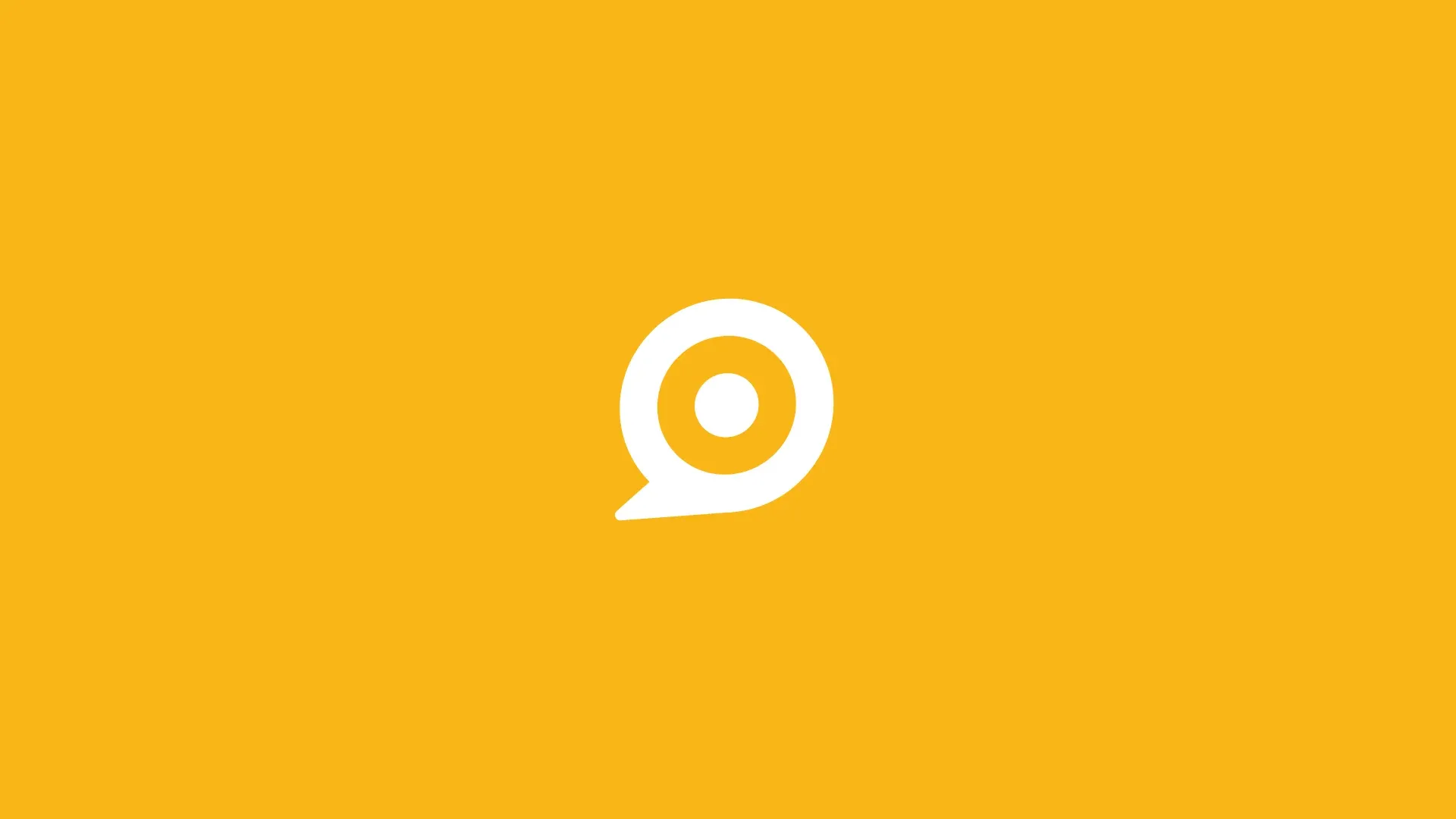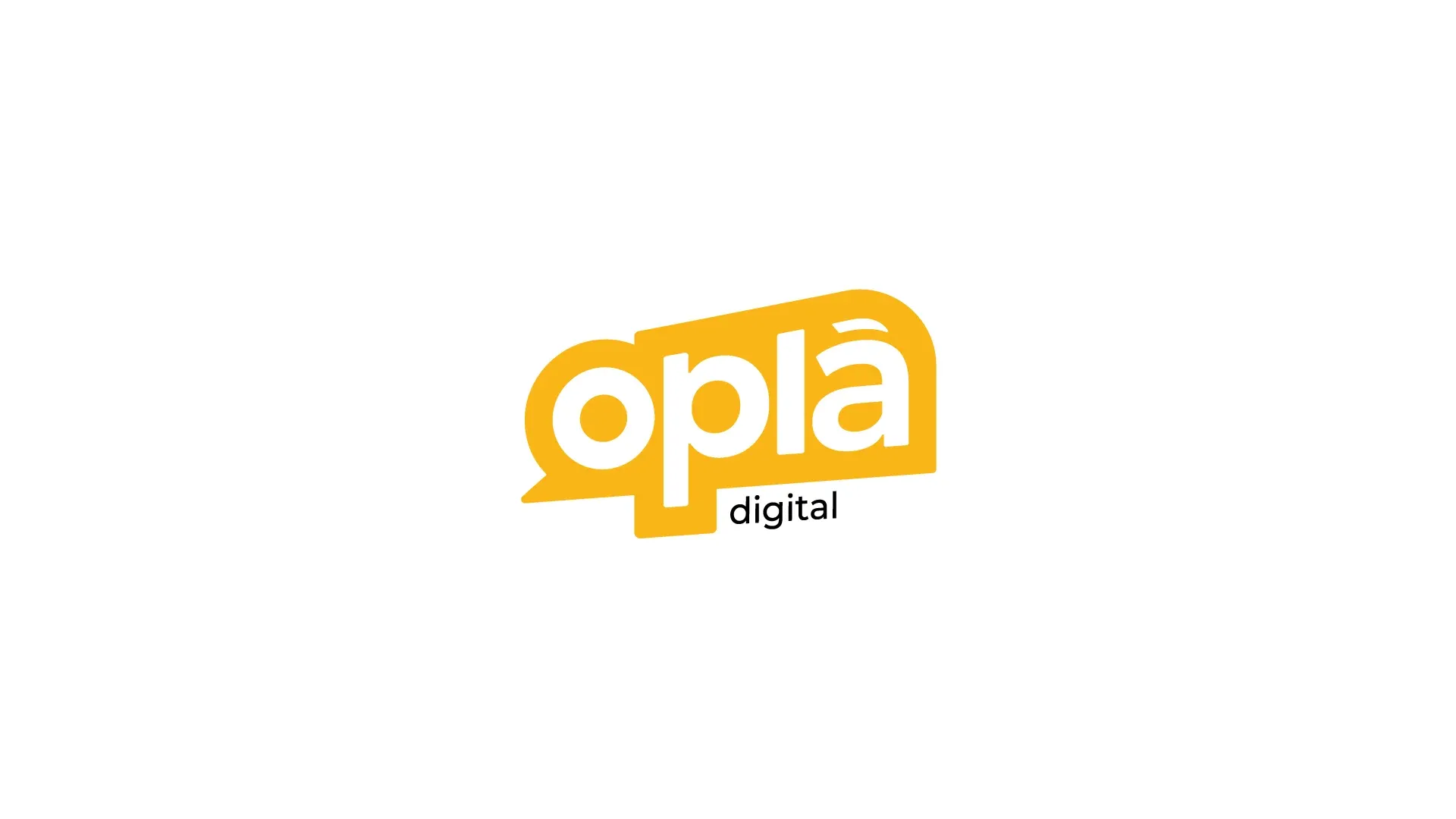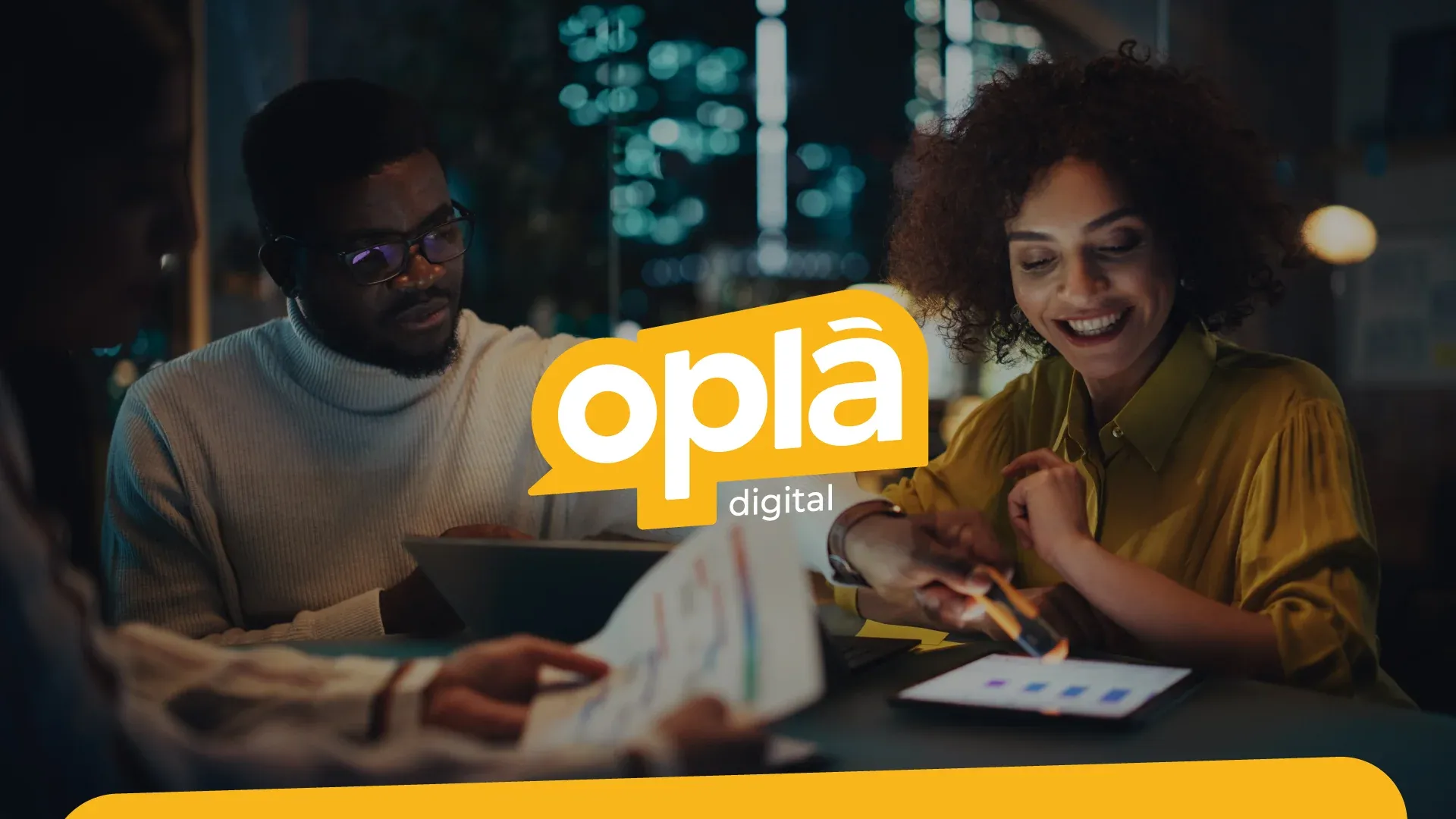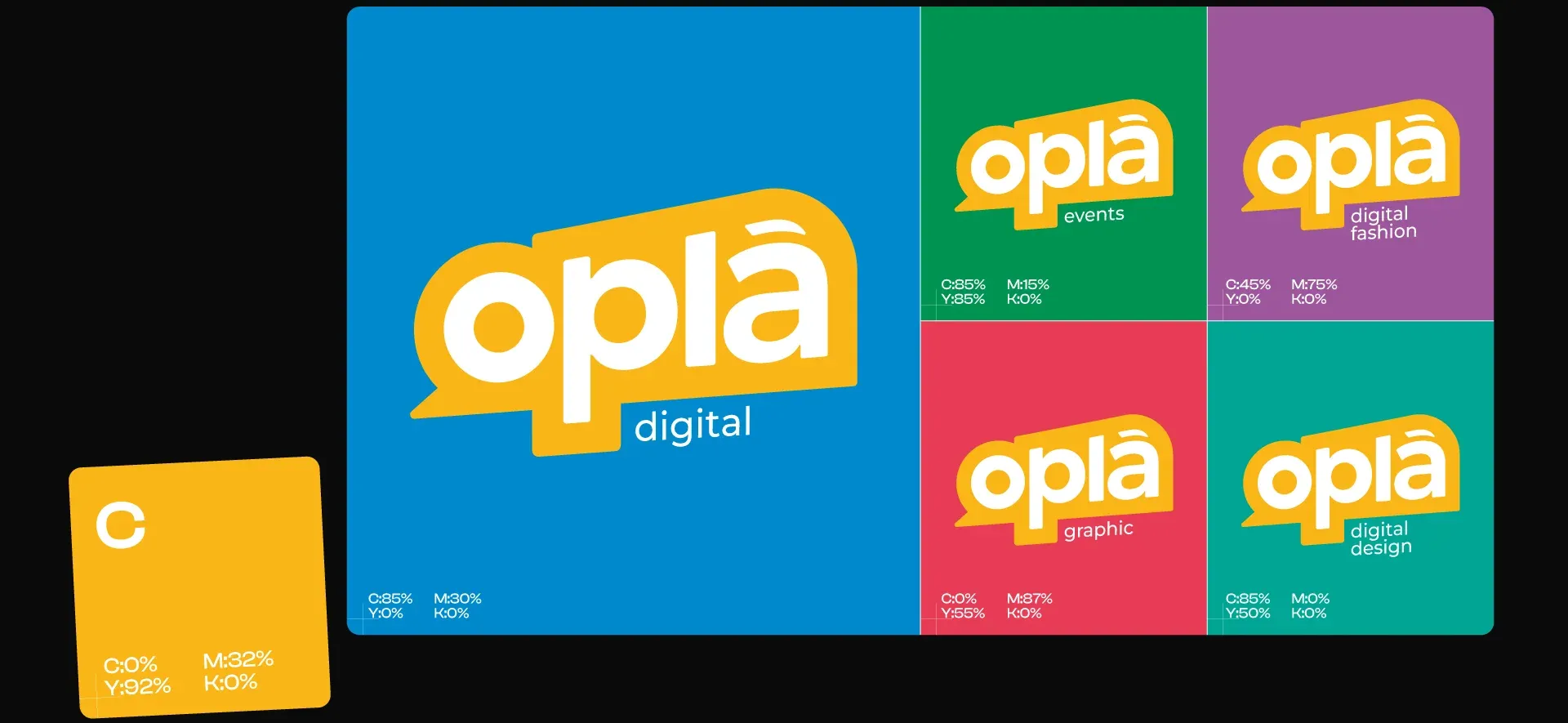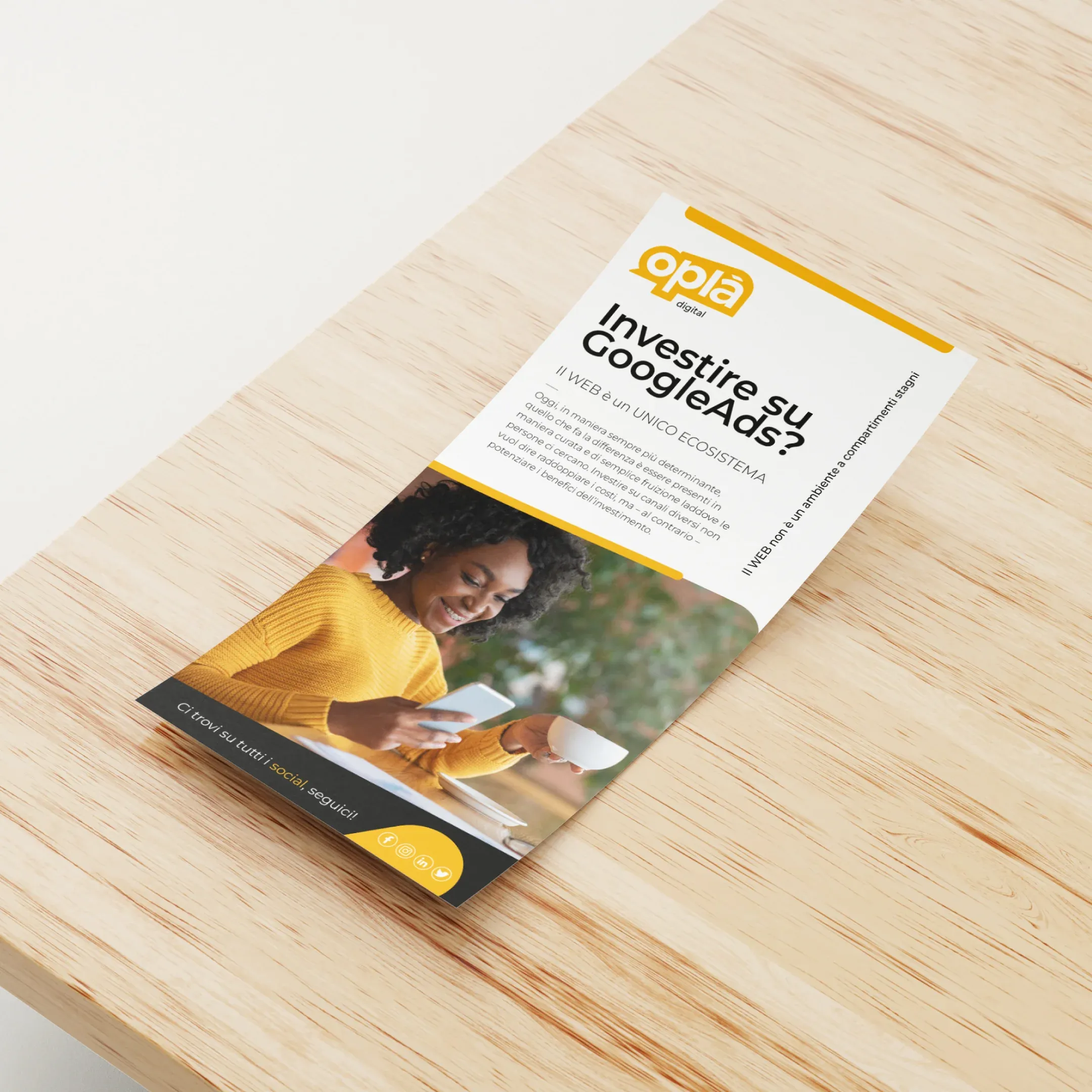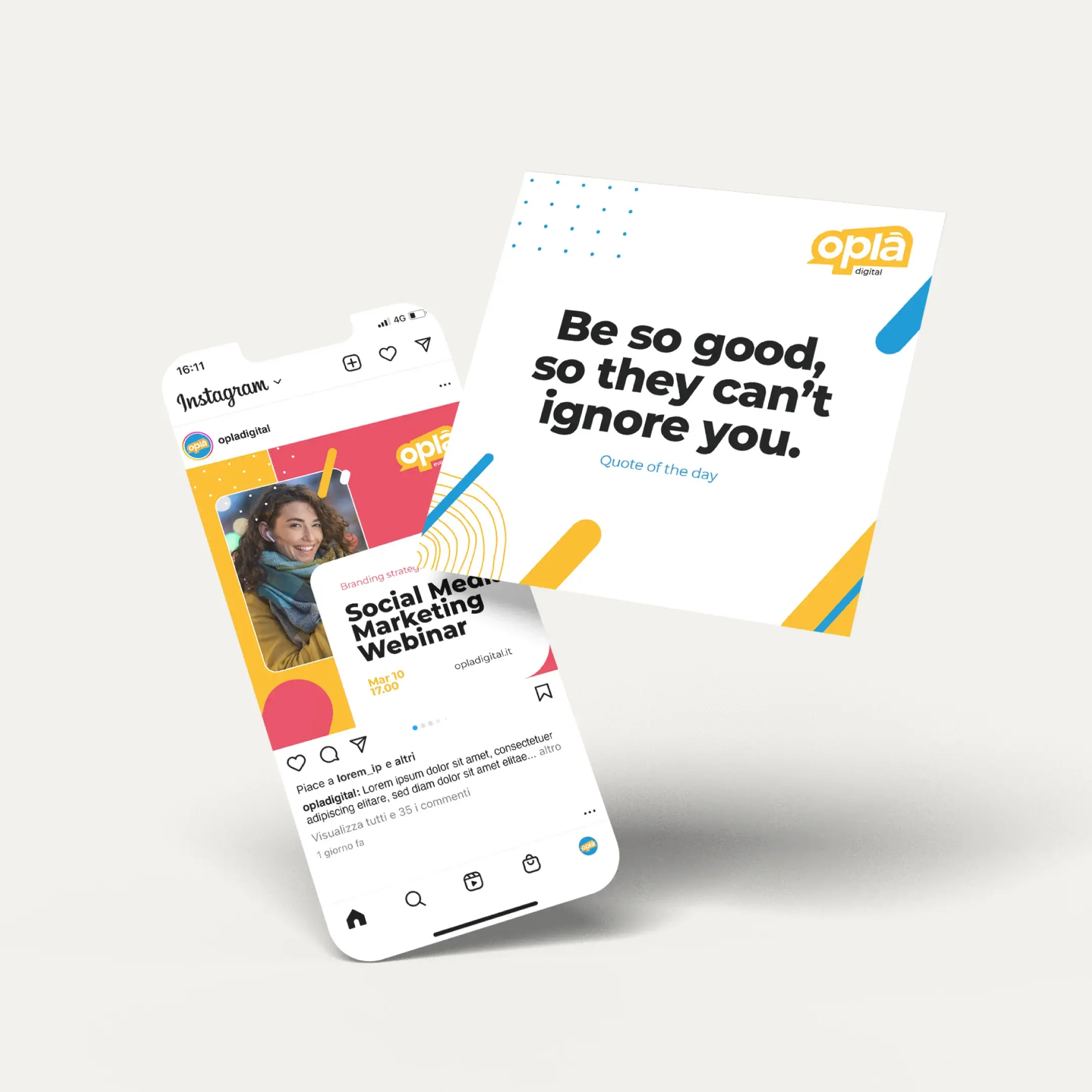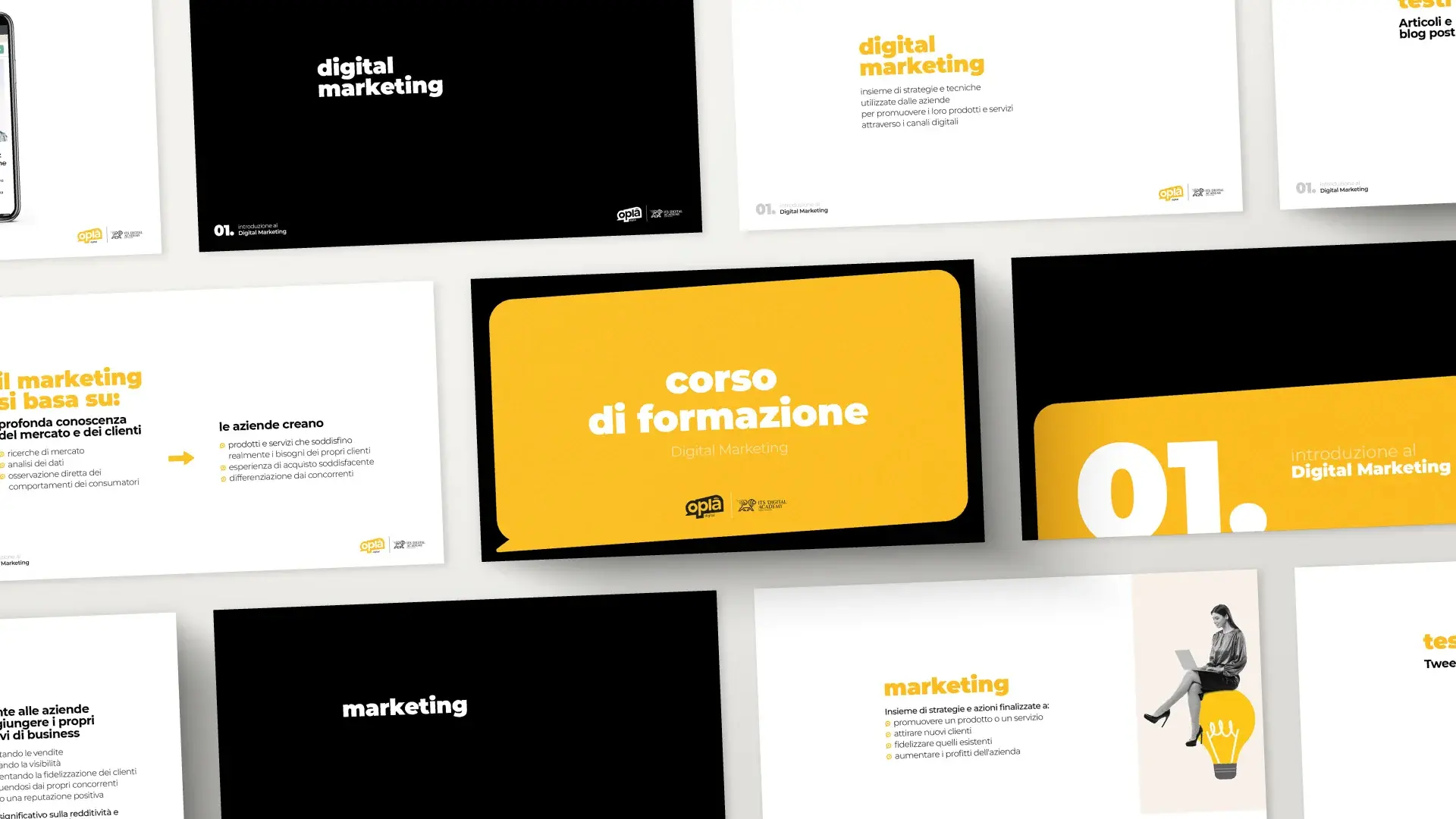
Brand identity per Oplà Digital
Oplà Digital è l'unione di tre freelance con competenze complementari, che offrono un servizio solido e strutturato nell'ambito del Digital Marketing. Per il loro progetto di restyling, ci siamo concentrati su diverse richieste, con l'obiettivo principale di rinfrescare il loro visual e renderlo immediatamente percepibile come fresco e attuale.
Rivisitazione del Logo
Abbiamo iniziato con la rivisitazione del logo, seguendo il loro mood e cercando di trasmettere il senso di "Oplà" come un'esclamazione. Il logo è stato trasformato in un baloon cartoon, enfatizzando e collegando così la parte visiva al loro principale ambito di lavoro: la comunicazione.
Adattabilità per Tematiche Future
Per rispondere alla richiesta di un logo versatile che si adatti a eventuali tematiche future, abbiamo creato un design creativo che associa il loro colore principale, il giallo, a cromie moderne, accattivanti e giovanili. Questo approccio garantisce che il logo possa evolversi con l'azienda e rimanere sempre attuale.
Grafica per Presentazioni
In aggiunta, abbiamo realizzato una base grafica per le loro presentazioni. Questo template può essere utilizzato liberamente durante incontri o lezioni, garantendo che la pulizia e la comunicazione degli elementi utilizzati riflettano ulteriormente il loro spirito fresco e attuale.